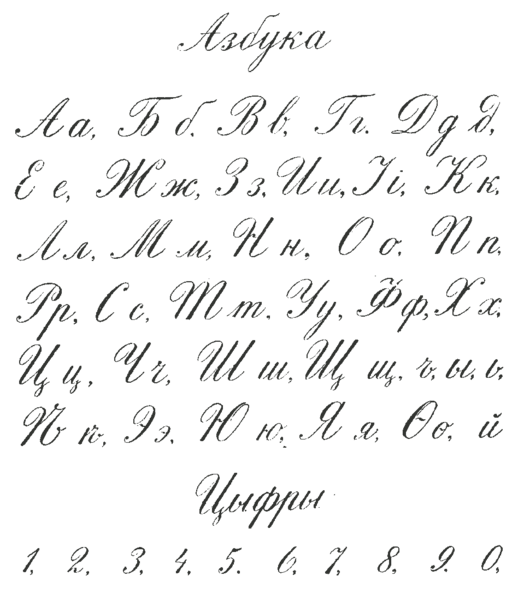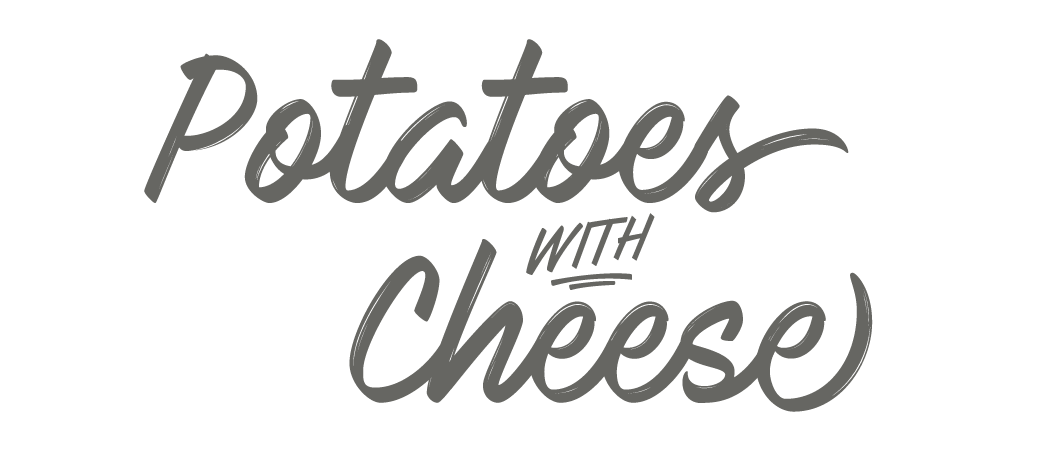
Кириллические рукописные шрифты в дизайне сайта
Нравятся рукописные шрифты, но считаете что они не впишутся в дизайн вашего сайта? Несмотря на все свои витиеватости и завитушки, рукописные шрифты могут отлично смотреться в заглавии, в тексте или в дизайне логотипа. Они отлично сочетаются с другими шрифтами и притягивают к себе внимание даже если выступают в роли второго, дополнительного шрифта.
А для того, чтобы вы в этом удостоверились, мы сделали подборку дизайнов, в которых кириллические рукописные шрифты очень органично смотрятся в дизайне.
Рукописные шрифты в дизайне
Посмотрите, как можно использовать рукописные шрифты в оформлении страниц сайтов или логотипах.
Меню на сайте кондитерскойНадпись на Главной странице и буквенный логотип сайта пекарни
Буквенный логотип магазина органической еды
Второй шрифт в дизайне сайта ресторана
Рукописный шрифт в дизайне гастрономического интернет-магазина
Заглавный шрифт в Keynote презентации
Бесплатные кириллические рукописные шрифты
Вдохновившись идеями для использования рукописных шрифтов, предлагаем вам выбрать один из предложенных ниже и смело использовать в своём проекте.
Рукописный шрифт обязательно добавит уникальности вашему сайту и понравится пользователям. Он сразу привлечет внимание среди шрифтов семейства Sans Serif.
Кириллический шрифт Arabella Medium
Кириллический шрифт FK Aladdin
Кириллический шрифт LifeIsStrangeRU
Кириллический шрифт Brush Flair Cyr
Кириллический шрифт Intro Script R h3 Base
Кириллический шрифт LainyDay
Кириллический шрифт Angelface [Rus by me]
Кириллический шрифт Poetica Chancery
Кириллический шрифт BetterTogether-Script
Как создать собственный рукописный шрифт
В интернете в свободном доступе имеются сотни самых разных шрифтов, в том числе экзотических и рукописных, но даже такое их обилие окажется совершенно бесполезным, если вам нужен шрифт, имитирующий ваш собственный почерк.
Оказывается, что очень просто. Для этого понадобиться программа High-Logic FontCreator и немного усидчивости и терпения.
Некоторые полезные сведения
Если по такой ячейке кликнуть два раза, программа откроет символ в небольшом окошке, имеющем разметку в виде сетки с направляющими.
Захватывая мышкой маркеры, можно изменять размер шрифта, его высоты и ширину, угол наклона, а также форму самих контуров.
Что касается направляющих. В FontCreator их семь: WinDescent, BaseLine, x-Height, CapHeight, WinAscent и ещё две вертикальных без имени.
• BaseLine — опорная линия привязки, на которой «стоит» шрифт.
• CapHeight — определяет высоту заглавных букв.
• X-Height — определяет высоту строчных букв. Исключение составляют строчные буквы рукописных шрифтов, имеющие вверху «хвостик». Высота таких символов определяется линией CapHeight.
• Безымянные вертикальные линии определяют ширину символа. Для каждого символа она своя.
Мы можем об этом даже не подозревать, но все эти линии учитываются текстовыми редакторами, благодаря чему буквы в тексте не наслаиваются друг на друга, не располагаются одна выше другой, а стоят ровно, как вымуштрованные солдаты на параде.
Создание собственного рукописного шрифта
Возьмите обычный лист белой бумаги формата А4 и напишите на нём в ряд все буквы (строчные и заглавные), а также все символы, которые вы предполагаете использовать при печати. Писать лучше всего чёрной гелевой ручкой, чтобы символы на листе были чёткими и хорошо выделялись. Далее сканируем лист в изображение формата
Далее открываем какой-нибудь кириллический шрифт в FontCreator, а полученное изображение — в любом графическом редакторе с поддержкой выделения. Для этого вполне сгодится Paint.